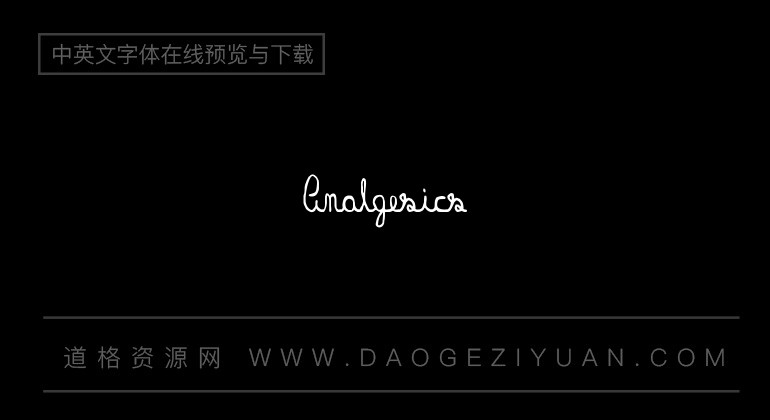
Analgesics
Analgesics 字体是一种简洁、优雅的英文字体,它具有细腻、精致的线条,使用它可以创造出清新、活泼的设计效果。Analgesics 字体具有极高的可读性,它的字母间距和字体结构能够提高文本的可读性,使得文本更加清晰。Analgesics 字体具有较高的灵活性,它可以在任何尺寸上使用,而且可以在任何类型的环境中使用,从而能够更好地满足不同的设计需求。
Analgesics是一款非常不错的手写艺术字体,具有很好的视觉感,适合于文化类的宣传设计、商业类品牌的广告和产品包装设计以及个性化文字排版等较多场景。